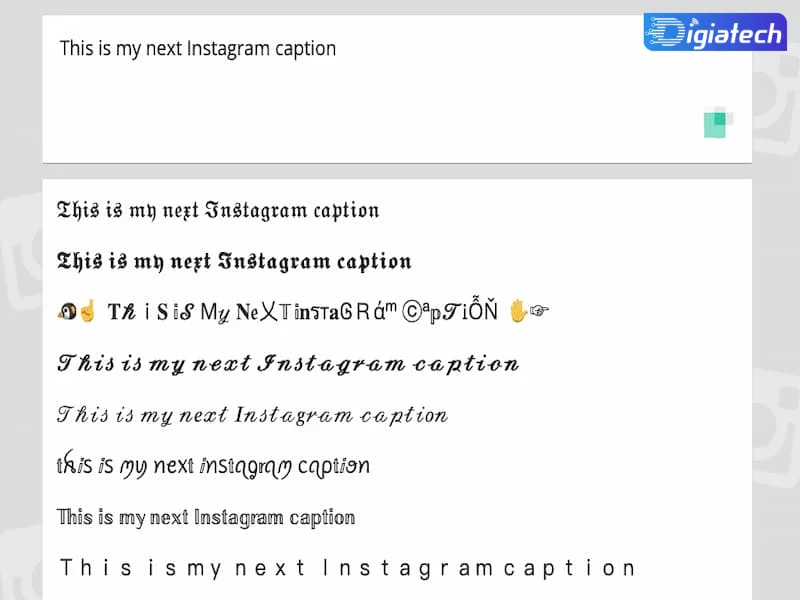
آموزش اضافه کردن فونت دلخواه به استوری اینستاگرام
آموزش اضافه کردن فونت دلخواه به استوری اینستاگرام و انواع فونتهایی که اینستاگرام در حال حاضر استفاده میکند را در این مطلب از دیجیاتک برای شما همراهان همیشگی این رسانه آنلاین قرار داده ایم. با ما همراه باشید.
فونت اینستاگرام چیست ؟
همانطور که گفتیم اینستاگرام یک برنامه تصویر محور است.
با این حال تاثیر کلمات را نباید در این شبکه اجتماعی دست کم گرفت.
چه در کپشن پستهای اینستاگرام و چه در استوریها، شما میتوانید از فونت اینستاگرام استفاده کرده و چیزهایی که میخواهید را بنویسید.
اما شاید برای شما سوال باشد که فونت اینستاگرام چیست و اینستاگرام چه فونتهایی دارد.
اینستاگرام در مقایسه با سایر شبکههای اجتماعی روز به روز محبوبیت بیشتری پیدا میکند.
این موضوع به این دلیل است که توسعه دهندگان برای تجسم بهتر محتوای برنامه تلاش زیادی کردهاند.
فونت اینستاگرام ممکن است بسته به سیستم عاملی که در آن از این برنامه استفاده میکنید، متفاوت باشد.
به عنوان مثال، اگر اینستاگرام را در دستگاههای ای او اس باز کنید، فونت Freight Sans و Niue Helvetian را مشاهده خواهید کرد.
در دستگاههای اندرویدی، ترکیبی از Roboto و Fright وجود دارد. به طور مشابه، اگر از نسخه وب اینستاگرام استفاده میکنید، فونت Proxima Nova را برای هر منظوری در آنجا خواهید دید.
ما به طور عمیق به انواع فونتهایی که اینستاگرام در حال حاضر استفاده میکند، نگاهی خواهیم کرد:
فونت Proxima Nova
فونت پروکسیما نوا در سال ۲۰۰۵ توسط مارک سیمونسون منتشر شد.
این نوع فونت یک نوع فونت بسیار معروف است. میتوان گفت که این نوع فونت ترکیبی از Futura و Akzidenz Grotesk است که برخی از اضافات مدرن در آن وجود دارد.
هفت نوع از این نوع فونت وجود دارد. این انواع شامل نازک، سبک، منظم، نیمه پررنگ، پررنگ، سیاه و پررنگ هستند.
متن نوشته شده در پروکسیما نوا زیبا به نظر میرسد.
فونت Roboto
ربوتو یک فونت حیاتی و پرکاربرد است. این فونت پیش فرض اندروید است.
این نوع فونت در سال ۲۰۱۱ منتشر شد. سه نوع از ربوتور وجود دارد:
حروف لاتین، یونانی و سیریلیک. روبوتو انواع فونتهای زیادی دارد که میتوانید با توجه به نیاز خود انتخاب کنید.
این فونت یکی از انواع فونتهای ساده است که دیدن آن خوب است.
فونت Freight Sans
اگر میخواهید از یک نوع فونت ساده استفاده کنید، Freight Sans میتواند بهترین انتخاب باشد.
شما قطعا از دیدن ظاهر خوب آن احساس خوشحالی خواهید کرد. این نوع فونت برای نوشتن کتاب مناسب است.
Neue Helvetica
Neue Helvetica یک نوع فونت معروف است که توسط Max Miedinger طراحی شده است.
این نوع فونت متعلق به تایپ فیسهای شناخته شده در دنیاست.
این فونت عمدتا در نوشتن نام مغازهها، شرکتهای فناوری، تابلوهای عمومی و لوگوهای آیفون استفاده میشود.
چرا باید فونت اینستاگرام خود را عوض کنید؟
متمایز شدن
اینستاگرام یکی از خلاقانهترین شبکههای اجتماعی است.
بسیاری از طراحان، خالقان، هنرمندان از آن برای نمایش آثار خود استفاده میکنند.
بهطور مشابه، بسیاری از برندها نیز با برجسته کردن خلاقیت خود برای جلب توجه رقابت میکنند.
این بدان معنی است که سطح رقابت از نظر خلاقیت فوق العاده بالا است. ا
ستفاده از فونتهای سفارشی و تغییر فونت استوری اینستاگرام یکی از راههایی است که میتوانید حضور خود در اینستاگرام را از دیگران متمایز کنید.
برای به نمایش گذاشتن خلاقیت
اینستاگرام تماما در مورد آزمایش محبوبیت محتوای شماست، اینطور نیست؟
پلتفرم رسانههای اجتماعی راههای زیادی برای انجام این کار ارائه میدهد.
تغییر فونت متن و تغییر فونت فارسی اینستاگرام راه دیگری است که میتوانید خلاقیت خود را به نمایش بگذارید.
همگام شدن با جریان روز
یکی دیگر از چیزهای باورنکردنی در مورد اینستاگرام سرعت ظهور روندهای جدید در این پلتفرم است.
بنابراین اجازه دهید با آن روبرو شویم، کارهایی مانند تغییر فونت فارسی اینستاگرام روی کلیت این پلتفرم نیز تأثیر خواهند گذاشت.
فقط تصور کنید که برای مدت طولانی به یک روند پایبند باشید.
در نهایت، فالوورهای شما پروفایل شما را قدیمی و عقب مانده خواهند دید.
استفاده از فونتهای سفارشی در اینستاگرام در حال حاضر در میان اینفلوئنسرها و برندها رواج دارد. این بدان معنی است که زمان آن رسیده که شما نیز آن را امتحان کنید.
اضافه کردن فونت و افزایش فالوور
همانطور که بیان کردیم، شما با اضافه کردن فونت در اینستاگرام، نسبت به کاربران دیگر متمایز خواهید شد و در واقع این امر می تواند به برندسازی شما کمک شایانی کند.
فالوورهای شما هنگامی که به استوری شما برسند و تغییر را احساس کنند، از روی کنجکاوی نیز ممکن است در استوری شما مکث کنند و همین امر به هوش مصنوعی اینستاگرام پیامی را ارسال می کند که محتوای شما ارزش بالایی دارد.
علاوه بر این، با تغییر فونت استوری اینستاگرام، کاربران نیز از روی فونت پیج شما را شناسایی می کنند و شما نیز از این طریق می توانید الگوی مشخصی را برای تولید محتوای خود بسازید.
همین امر می تواند تاثیر زیادی در تعامل با کاربرانتان داشته باشد و در آخر نیز افزایش فالوور را به همراه می آورد.
اضافه کردن فونت به اینستاگرام چگونه است؟
برای اینکه به اینستاگرام خود فونت اضافه کنید و فونت استوری های خود را تغییر دهید، باید یک نرم افزار ثانویه نصب کنید.
چرا که برنامه اینستاگرام به تنهایی چنین قابلیتی ندارد.
در این زمینه برنامه های گوناگونی طراحی شده اند و هر کدام از این برنامه ها دارای معایب و مزایای خاص خودشان هستند.
در ادامه قصد داریم برخی از آنها را به شما کاربران عزیز معرفی کنیم
برنامه را نصب و اجرا کنید.
روی قسمت دوم کلیک نمایید و سپس گزینه edit را انتخاب نمایید.
متن دلخواه خودرا وارد کنید و گزینه فونت را لمس کنید و فونت دلخواه خودرا انتخاب نمایید.
با انتخاب گزینه Color رنگ متن را تغییر دهید.
در آخر متن را ذخیره کنید.
نتیجه
در این مقاله به تغییر فونت در برنامه اینستاگرام پرداختیم.
شما می توانید از این طریق محتوای جذاب و زیبایی را تولید و منتشر کنید.
اگر قصد دارید محتوای جذابی را تولید نمایید و فالوورهای بیشتری را به سمت پیج خود بکشانید، باید تلاش کنید از فونت های متفاوتی استفاده کنید.